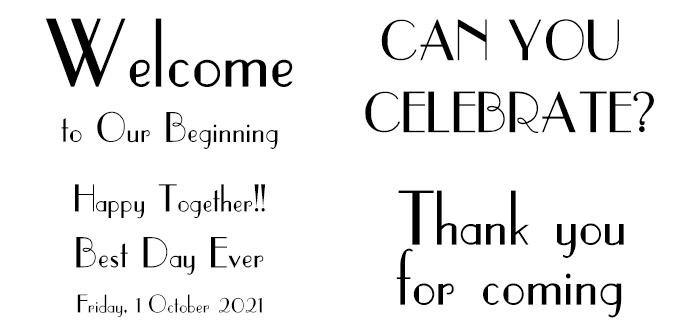
結婚式に合うフォント 特化型 目的別フォントガイド
結婚式に合うフォント:特化型 目的別フォントガイド #023
今回は結婚式に合うフォント。日々フォントのことばかり考えている当店スタッフが直感的に選んだフォントをご紹介します。
結婚式に合うフォントをスタッフが選びました
結婚式に合うフォント #1 TA-金木犀_黒 (大崎善治)
TA-金木犀_黒 (大崎善治) 【FONT1000】
手で丁寧に書いたようなフォントでどのようなお知らせにも似合うようなフォントだと思い選びました。
結婚式に合うフォント #2 こまどり+
こまどり+【ヤマナカデザインワークス】
主張しすぎないロゴタイプ。厳かな中にも可愛らしさをプラスしてください。
結婚式に合うフォント #3 堀内正楷書
堀内正楷書 【堀内湖洲フォント】
招待状、宛名、プロフィール紹介など、丁寧できれいな文字が欲しい時にピッタリの楷書体。和テイストのモノで縦書きでもバランスが良いです。
結婚式に合うフォント #4 花とちょうちょ
花とちょうちょ【鈴木メモ】
晴れの日の結婚式にぴったりなデザインの手書きフォントです。
結婚式に合うフォント #5 DF娥眉明朝体 W7
DF娥眉明朝体 W7【ダイナフォント】
細長く弧を描いた眉の形をイメージしたストロークから洗練された女性の柔らかさや優しさを表現した明朝体。清潔感や高級感あるデザインで、高級感のある結婚式の招待状やウェルカムボードにピッタリなフォントです。
結婚式に合うフォント #6 DF古籍銀杏 AW3
DF古籍銀杏 AW3【ダイナフォント】
半円形となったストロークが繊細で、銀杏の葉っぱのような優雅さがある明朝ベースの書体です。文字の重心が高く穏やかで、古籍ならではの情緒が視覚的な美しさを引き立てるので、結婚式の招待状やウェルカムボードにピッタリなフォントです。
結婚式に合うフォント #7 ウエルカムボード用欧文 AF-WelcomeBoard
ウエルカムボード用欧文 AF-WelcomeBoard【フォントユーコム】
ウェルカムボードをオシャレにしてくれる欧文書体。何と言っても880円の安さが嬉しいですね!
結婚式に合うフォント #8 Banana
Banana【Dharma Type】
重くて丸みを帯びたフォルムが印象的なブラッシュ系のスクリプト体。直立した線とその形状の広い幅は、簡単でゆっくりとした印象を与え、リラックスした雰囲気の結婚式の招待状やウェルカムボードのデザインに最適なフォントです。
結婚式に合うフォント #9 Wola™ Regular
Wola™ Regular【Monotype】
Bodoniをベースに手書きのようにデザインしたハンドライト系のスクリプト体。手作り感が温かみのある印象を与え、親しみのあるデザインの結婚式の招待状やウェルカムボードに最適なフォントです。
結婚式に合うフォント #10 Snell Roundhand® Std Bold
Snell Roundhand® Std Bold【Linotype】
17世紀後半のイギリスのレタリング名手の書体を再現したフォーマルなスクリプト体の定番フォントです。高貴で優雅な印象を与えるデザインで、高級感のある結婚式の招待状やウェルカムボードのデザインにピッタリなフォントです。
結婚式に合うフォント #11 Zapfino® Extra Pro Regular
Zapfino® Extra Pro Regular【Linotype】
1998年にドイツのカリグラファーによりデザインされたフォーマルなスクリプト体の定番フォントです。より手書きに近い造形を目指して自由な形でデザインが優雅な印象を与え、高級感のある結婚式の招待状やウェルカムボードのデザインにピッタリなフォントです。
結婚式に合うフォント #12 Polonaise Bold
Polonaise Bold 【URW Type Foundry】
70年代のLPジャケットに使われていそうなクラシックな欧文手書き風フォント。大文字の曲線が美しいので、ウエルカムボードや招待状など、いろんな場面で利用できる万能さがあります。